Font chữ là một trong những yếu tố quan trọng nhất trong thiết kế đồ họa. Một font phù hợp không chỉ giúp truyền tải thông điệp hiệu quả mà còn tạo nên dấu ấn riêng cho thương hiệu, sản phẩm hoặc chiến dịch truyền thông. Đối với designer, việc sở hữu một bộ sưu tập font chất lượng là điều không thể thiếu trong quá trình sáng tạo. Nếu bạn đang tìm kiếm những font đẹp, chuyên nghiệp và dễ ứng dụng trong nhiều dự án khác nhau, bài viết này sẽ giúp bạn khám phá những lợi ích khi Tải Font Chữ miễn phí cũng như cách lựa chọn font phù hợp cho từng nhu cầu thiết kế.
Tại Sao Font Chữ Quan Trọng Trong Thiết Kế?
Typography đóng vai trò quan trọng trong việc tạo nên trải nghiệm thị giác của người xem. Một font chữ đẹp có thể làm nổi bật nội dung, tăng khả năng nhận diện thương hiệu và giúp thiết kế trở nên chuyên nghiệp hơn.
Bên cạnh màu sắc, hình ảnh và bố cục, font chữ là yếu tố giúp định hình phong cách tổng thể của sản phẩm. Từ thiết kế logo, poster, banner cho đến giao diện website, việc lựa chọn đúng font có thể tạo ra sự khác biệt lớn.
Lợi Ích Khi Sử Dụng Font Chữ Miễn Phí
Đa Dạng Phong Cách
Hiện nay có rất nhiều font miễn phí thuộc nhiều phong cách khác nhau như hiện đại, cổ điển, tối giản, sang trọng hoặc nghệ thuật. Điều này giúp designer dễ dàng lựa chọn kiểu chữ phù hợp với từng dự án.
Dễ Dàng Ứng Dụng
Những Loại Font Chữ Được Designer Yêu Thích
Font Serif
Font Serif là kiểu chữ có chân, thường mang lại cảm giác sang trọng, chuyên nghiệp và đáng tin cậy. Đây là lựa chọn phổ biến trong các dự án thiết kế thương hiệu, tạp chí hoặc sản phẩm cao cấp.
Một số ưu điểm của font Serif:
- Tạo cảm giác chuyên nghiệp.
- Dễ đọc trong các nội dung dài.
- Phù hợp với thiết kế cao cấp.
Font Sans Serif
Sans Serif là kiểu chữ không chân với phong cách hiện đại và tối giản. Đây là loại font được sử dụng rộng rãi trong thiết kế website, ứng dụng và các sản phẩm công nghệ.
Ưu điểm nổi bật:
- Thiết kế gọn gàng.
- Dễ đọc trên màn hình.
- Mang tính hiện đại cao.
Font Script
Font Script mô phỏng nét chữ viết tay và thường được sử dụng trong các thiết kế mang tính nghệ thuật hoặc cá nhân hóa.
Loại font này phù hợp với:
- Thiệp cưới.
- Logo thời trang.
- Thiết kế mỹ phẩm.
- Poster sự kiện.
Font Display
Display Font được thiết kế để tạo điểm nhấn mạnh mẽ cho tiêu đề hoặc các thành phần nổi bật trong bố cục.
Đặc điểm:
- Cá tính mạnh.
- Thu hút ánh nhìn.
- Phù hợp với thiết kế quảng cáo.
Những Tiêu Chí Khi Lựa Chọn Font Chữ
Phù Hợp Với Mục Đích Sử Dụng
Mỗi dự án sẽ yêu cầu phong cách font khác nhau. Ví dụ, font Serif thường phù hợp với thương hiệu cao cấp trong khi Sans Serif thích hợp với các sản phẩm công nghệ.
Đảm Bảo Khả Năng Đọc
Một font đẹp nhưng khó đọc sẽ làm giảm hiệu quả truyền tải thông điệp. Vì vậy, designer cần cân bằng giữa tính thẩm mỹ và khả năng đọc của font.
Hỗ Trợ Tiếng Việt
Đối với các dự án dành cho thị trường Việt Nam, nên ưu tiên những font có đầy đủ dấu tiếng Việt để đảm bảo tính chuyên nghiệp và nhất quán.
Các Ứng Dụng Thực Tế Của Font Chữ Trong Thiết Kế
Thiết Kế Logo
Font chữ là thành phần quan trọng trong việc xây dựng nhận diện thương hiệu. Một font phù hợp giúp logo trở nên nổi bật và dễ ghi nhớ hơn.
Thiết Kế Poster
Poster quảng cáo cần những font có khả năng thu hút sự chú ý ngay từ cái nhìn đầu tiên. Việc lựa chọn đúng kiểu chữ sẽ giúp thông điệp được truyền tải hiệu quả hơn.
Thiết Kế Bao Bì
Trên bao bì sản phẩm, font chữ không chỉ đóng vai trò hiển thị thông tin mà còn góp phần xây dựng hình ảnh thương hiệu.
Thiết Kế Website
Typography là yếu tố ảnh hưởng trực tiếp đến trải nghiệm người dùng. Các font hiện đại và dễ đọc sẽ giúp website chuyên nghiệp hơn.
Vì Sao Designer Nên Thường Xuyên Cập Nhật Bộ Font?
Xu hướng thiết kế luôn thay đổi theo thời gian. Những font mới thường mang phong cách hiện đại hơn và phù hợp với nhu cầu thị trường hiện tại.
Việc thường xuyên Tải Font Chữ mới giúp designer:
- Mở rộng khả năng sáng tạo.
- Theo kịp xu hướng thiết kế.
- Tạo ra các sản phẩm độc đáo hơn.
- Nâng cao chất lượng công việc.
Ngoài ra, việc sở hữu nhiều font khác nhau cũng giúp quá trình lựa chọn trở nên linh hoạt và hiệu quả hơn.
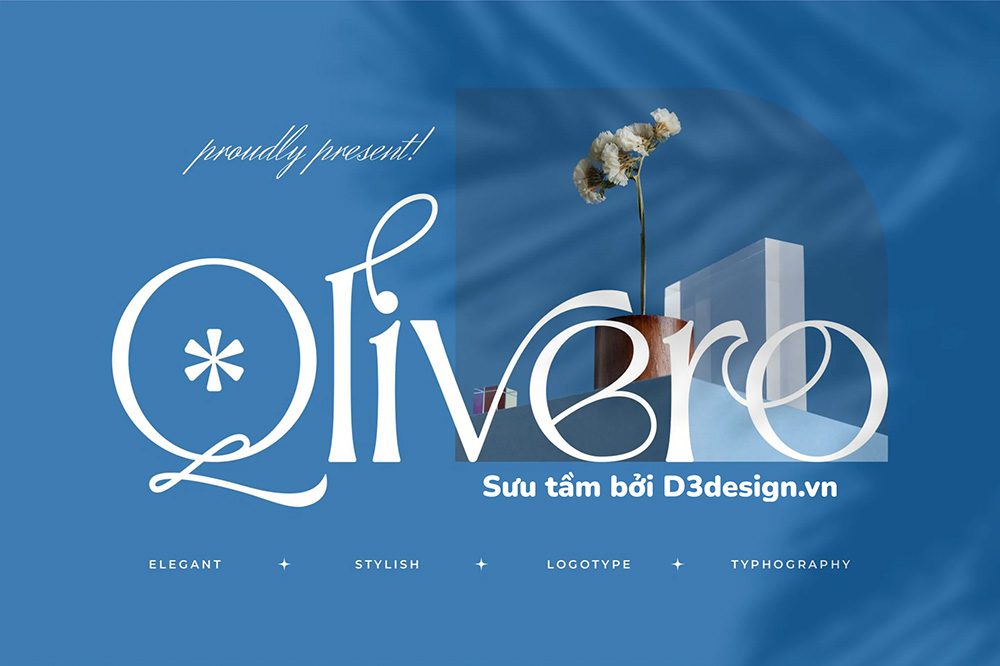
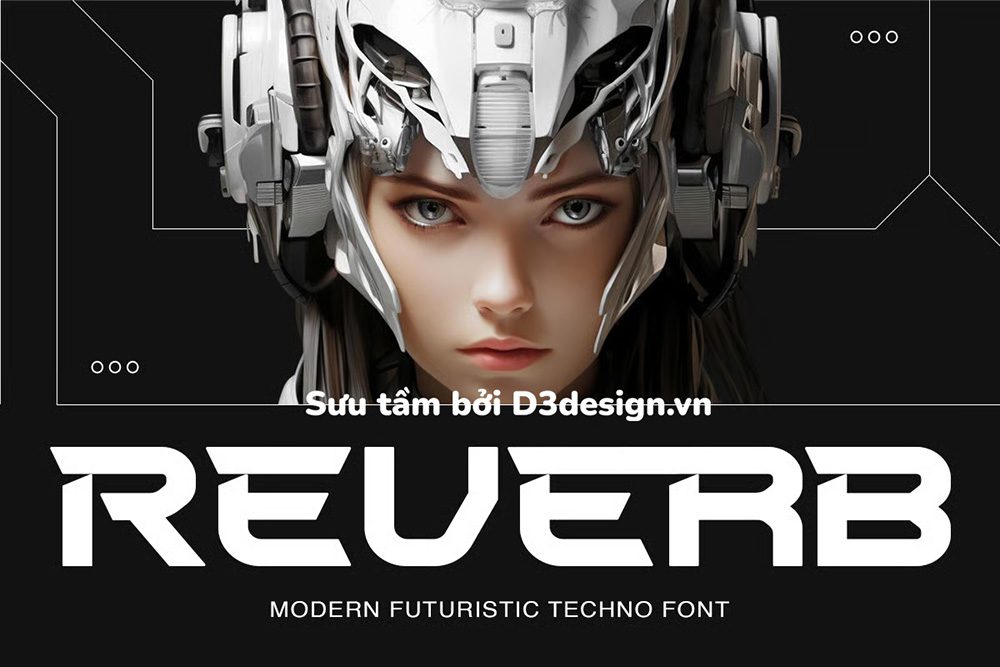
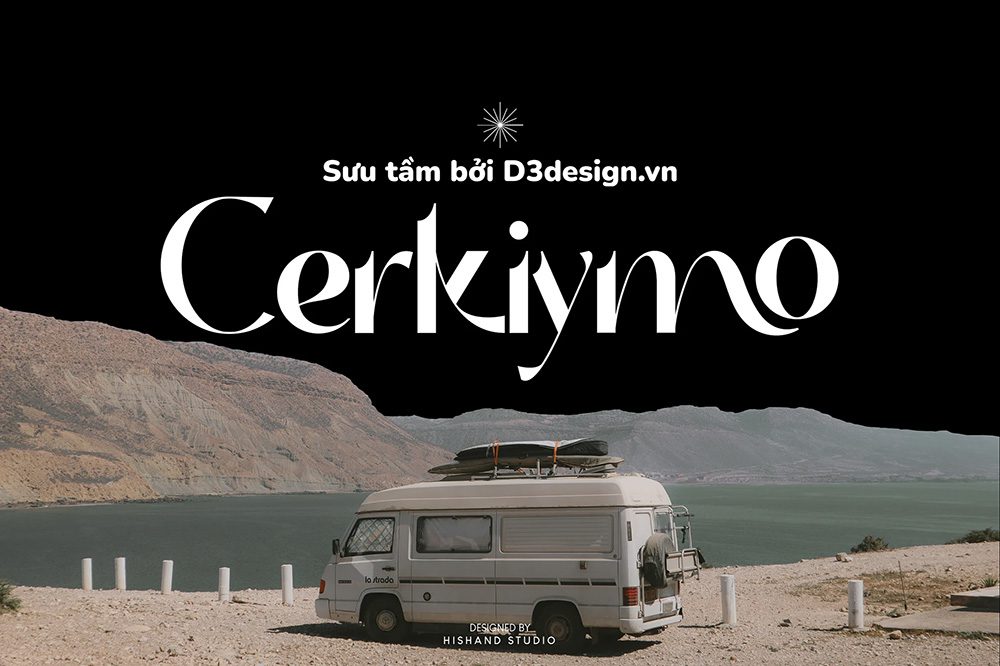
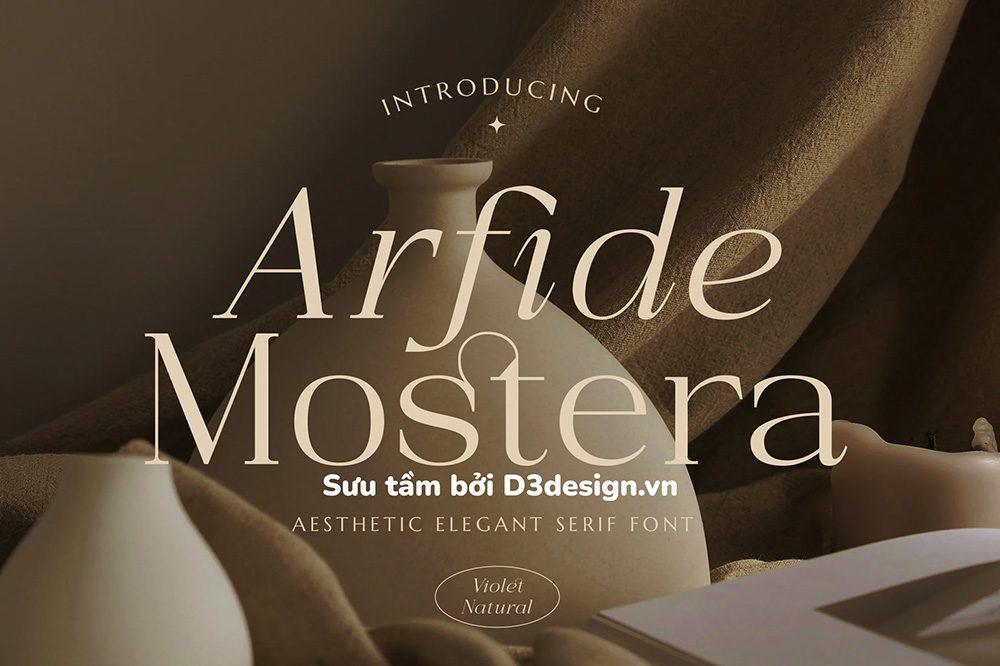
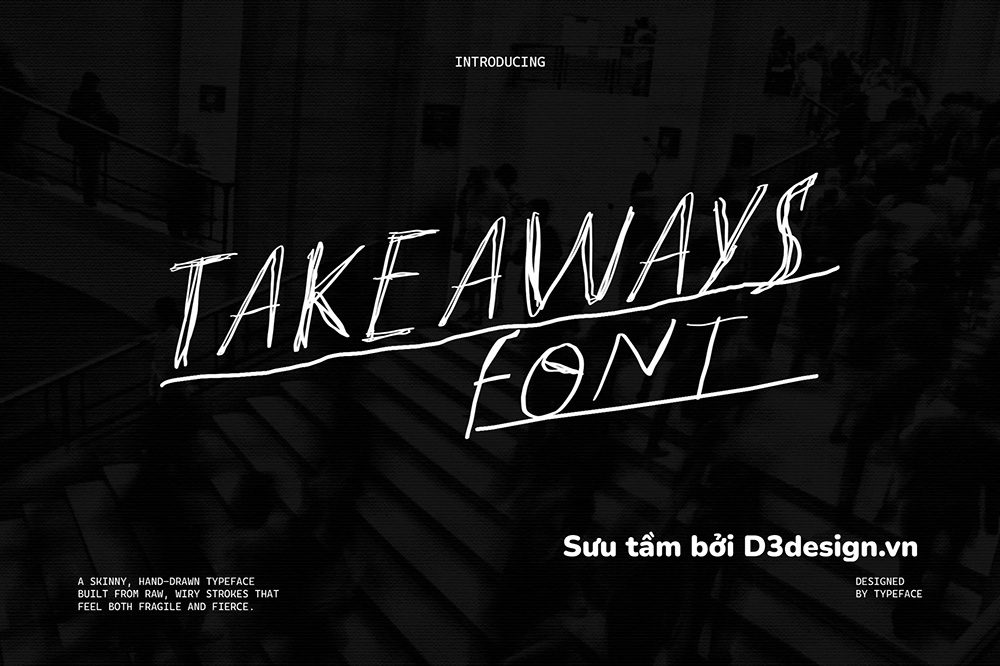
Kết Luận
Font chữ là một trong những yếu tố quan trọng nhất quyết định tính thẩm mỹ và hiệu quả truyền tải thông điệp trong thiết kế. Việc Tải Font Chữ miễn phí chất lượng cao không chỉ giúp tiết kiệm chi phí mà còn mang đến nhiều cơ hội sáng tạo cho designer. Với sự đa dạng về phong cách từ Serif, Sans Serif, Script đến Display, bạn hoàn toàn có thể tìm thấy những font phù hợp cho mọi dự án. Nếu muốn nâng cao chất lượng thiết kế và bắt kịp xu hướng mới, đừng quên thường xuyên Tải Font Chữ để bổ sung vào bộ sưu tập tài nguyên của mình.